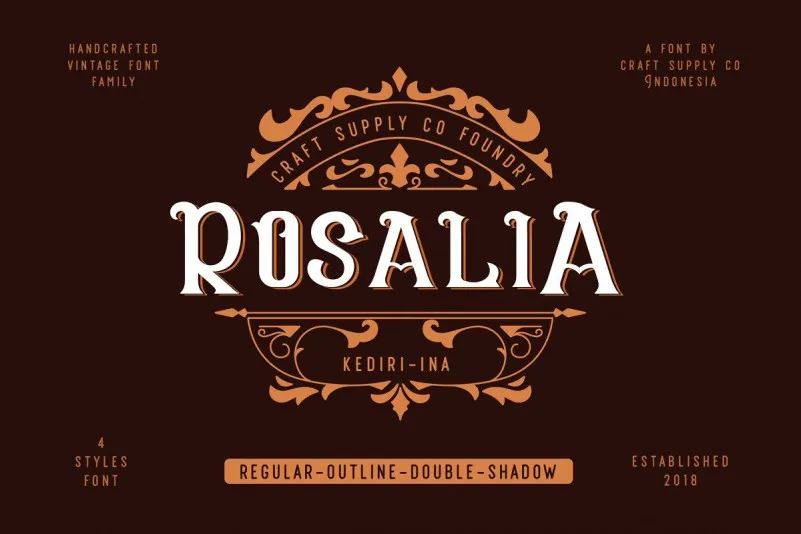
CS Rosalia Display Font – Download Grátis
A CS Rosalia Display Font é uma tipografia de rótulo vintage que se destaca especialmente para aplicações visuais. Suas quatro pesos tipográficos a tornam ideal para textos de exibição e projetos de design complexo. É uma fonte versátil, perfeita para criação de materiais impressos. Seus traços elegantes e distintivos podem ser usados para dar vida e vivacidade ao seu projeto gráfico. Com a CS Rosalia, você pode transformar qualquer projeto em algo inovador e impressionante. Sua criatividade se torna o centro do design com esta fonte única.